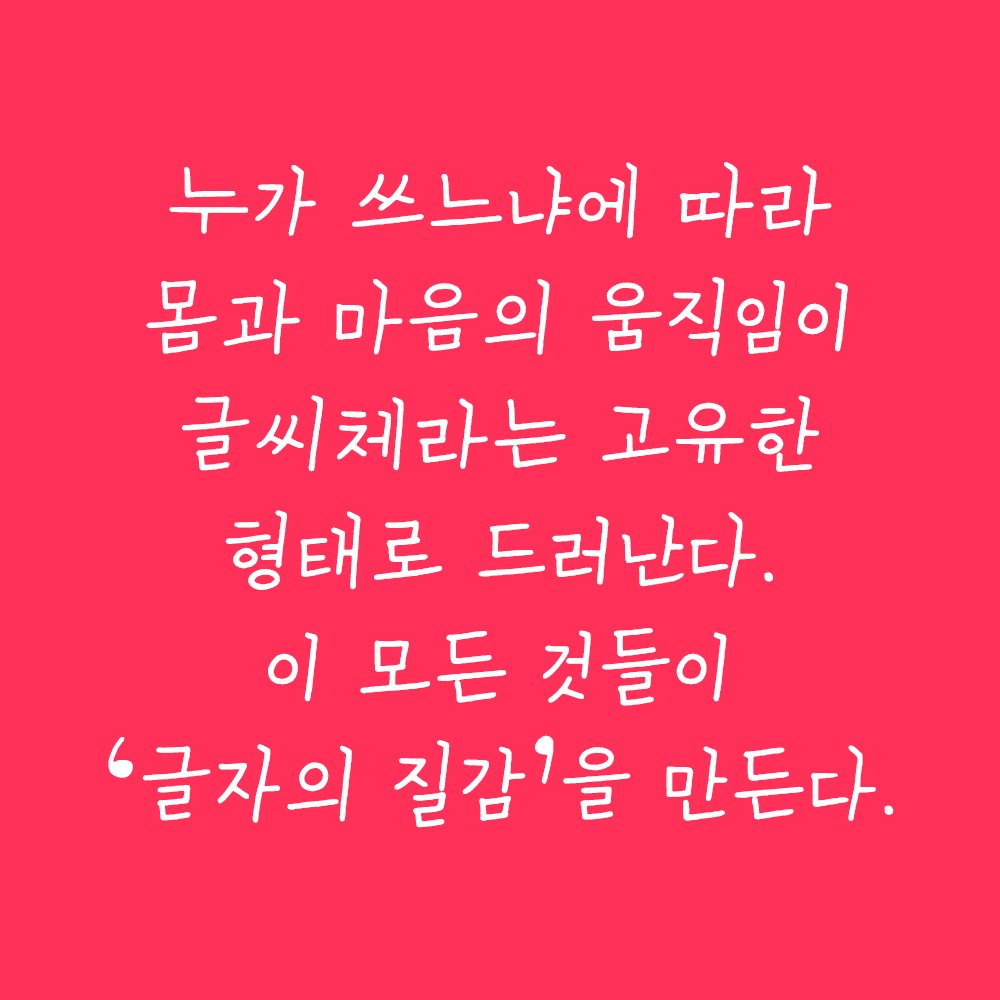
그리운X국한박 다흘체
GriunXHangeul DAHL
그리운X국한박 다흘체 소개
제5회 한글실험프로젝트 《글(자)감(각): 쓰기와 도구》 The 5th Hangeul Design Project 《Senses of Writing: Tools & Perception》 전시기간: 2025.11.19.~2026.3.22. 전시장소: 문화역서울284 RTO 주최·주관: 국립한글박물관 이 손글씨 폰트는 국립한글박물관 제5회 한글실험프로젝트 《글(자)감(각): 쓰기와 도구》 전시 연계 이벤트를 통해 제작되었습니다. 손의 움직임과 쓰는 감각을 그대로 담아, 쓰기의 경험을 폰트로 확장합니다.